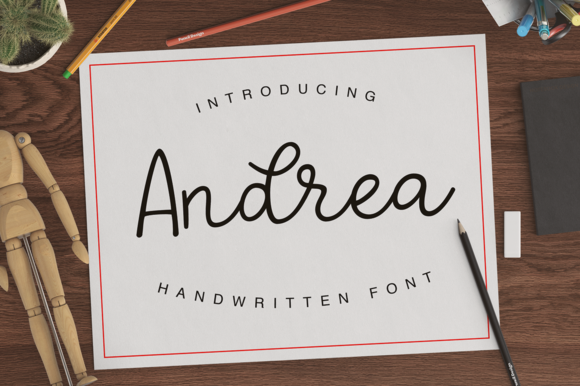
Andrea Script Font – Download Grátis
A fonte ‘Andrea Script Font’ é uma elegante fonte de escrita à mão, desenvolvida por Pasha Larin. Esta fonte monoline é ideal para quem quer adicionar um toque personalizado e sofisticado a suas criações gráficas. Com sua forma delicada e autêntica, Andrea é perfeita para aplicar em projetos de marca como cartazes ou materiais impressos, tornando-os ainda mais memoráveis e criativos. Além disso, ela se destaca quando usada em anúncios de casamento, headlines no blog e outros designs pessoais, oferecendo uma sensação única e autêntica ao texto. É também uma opção atraente para designers corporativos que desejam dar um toque especial à sua identidade visual. Obrigado a Creative Fabrica por liberá-la gratuitamente hoje para download.